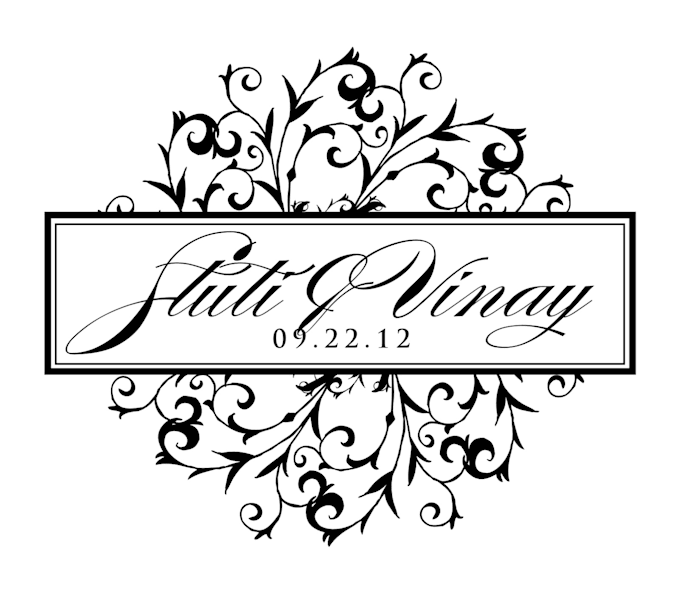
Хорошие шрифты для свадебных приглашений. ТОП 10 идей
Свадебные приглашения являются одним из основных пунктов в списке каждой невесты и жениха. Те, кто готовится к свадьбе, прекрасно знают, насколько важно и сложно подготовить идеальное приглашение . Есть, конечно, несколько факторов, которые следует учитывать при разработке этого типа уведомлений. Одним из них, и на самом деле самым важным, является красивый шрифт, который сделает наше приглашение стильным и оригинальным. Мы предлагаем вдохновение для самых красивых шрифтов для свадебных приглашений.
Свадебные приглашения — как выбрать?
Самое важное, что вы должны учитывать при выборе приглашений на свадьбу, это выбрать их в соответствии с темой вашей свадьбы . Если весь праздник должен быть гламурным, вы обязательно должны выбрать элегантное приглашение с красивым шрифтом. Свадьба в деревенском стиле должна быть объявлена с приглашением на экологической бумаге .
Однако все зависит от вашего творчества. Если вы хотите сойти с ума, вы всегда можете комбинировать стили в увлекательной игровой форме. Тот факт, что вы мечтаете о свадьбе в индустриальном стиле , не означает, что вы не можете позволить себе немного безумия или … подготовить элегантные приглашения, если вам не нравятся эти современные версии.
Мы рекомендуем вам подготовить свои собственные шаблоны приглашений . Конечно, сегодня на рынке можно найти различные варианты, и определенно есть из чего выбрать. Однако типографии предлагают вам возможность подготовить свои собственные проекты, благодаря которым вы можете представить свою личность и всю атмосферу запланированной вами церемонии по такому приглашению.
Свадебные приглашения — на что вы будете обращать внимание при выборе шрифта?
Этот шрифт нам нравится , это просто капля в океане, создающая приглашения.
Также следует обратить внимание на несколько важных элементов, которые, к сожалению, не все шрифты содержат.
- Шрифт должен быть разборчивым — некоторые шрифты написаны аккуратным курсивом, но при вводе текста с ними может оказаться, что он просто не читается. Если вы хотите, чтобы ваши гости прибыли в нужное место в определенное время, не заставляйте их угадывать, что написано в приглашении.
- Шрифт должен иметь польские символы — если ваше приглашение на польском языке, обязательно выберите шрифт, который содержит польские символы. Написание текста без них просто не будет выглядеть элегантно, не говоря уже о том, что это большая ошибка.
- Объедините шрифты — написание всего приглашения в декоративном шрифте может утомить ваше зрение. Особенно, когда шрифт очень оригинальный. Хотя деликатный курсив не будет мешать, лучше не писать полное приглашение, например, с помеченными словами. Объедините шрифты, чтобы выделить наиболее важные элементы, и попробуйте написать менее важную информацию (например, информацию о подарках или стихах) классическим шрифтом.
Хорошим решением также является изменение цвета шрифта, например, написание имен приглашенных людей другим цветом.
Свадебные приглашения — красивые шрифты для свадебных приглашений
Одним из наиболее важных элементов приглашения является, как уже упоминалось, шрифт . И выбор правильного является довольно сложной задачей. С огромным каталогом различных шрифтов выбор идеального может занять некоторое время. Особенно это соответствует стилю приглашения . Тем не менее, существуют различные популярные и элегантные варианты, на которые стоит обратить внимание.
Мы предлагаем список шрифтов, на которые стоит обратить внимание при подготовке свадебных приглашений.
1. Абсолют
2. Аллура
3. Афродита Слим Про
4. Осень в ноябре
5. Баскервиль Курсив
6. Сценарий Шопена
7. Coneria Script
8.
Великие флюиды
9. Монотип Корсива
10. Снелл
Calypsoka склоняется к непринужденной, игривой стороне, которая обязательно вызовет улыбку на лицах ваших гостей, когда они откроют конверт.